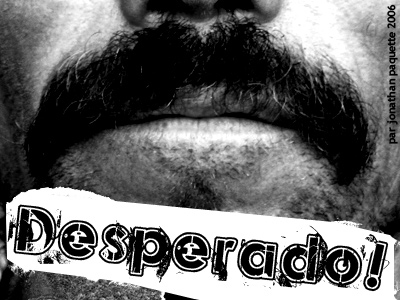
Desperado! von Jonathan Paquette ist eine kostenlose, verzerrte Display-Schrift, die aussieht, als hätte man sie durch Tinte, Asphalt und einen Kopierer gezogen. Die dicken, runden Buchstaben sind von zielscheibenartigen Kreisen durchsetzt und mit splittrigen Spritzern versehen, was jedem Wort eine raue, urbane Energie verleiht. Die Formen bleiben fett und lesbar, aber die abgewetzten Kanten und unvollständigen Füllungen verhindern, dass die Schrift jemals sauber oder brav wirkt.
Mit Desperado! wirken Ihre Titel sofort laut, chaotisch und ein wenig gefährlich – perfekt für Konzertplakate, Underground-Flyer, Album-Art, Horror- oder Action-Spiele, Skate-Marken und Zines. Diese kostenlose Schrift funktioniert am besten groß und fett; kombinieren Sie sie für den Fließtext mit einer schlichten, schmalen serifenlosen Schrift, damit die Grunge-Texturen für sich sprechen können.